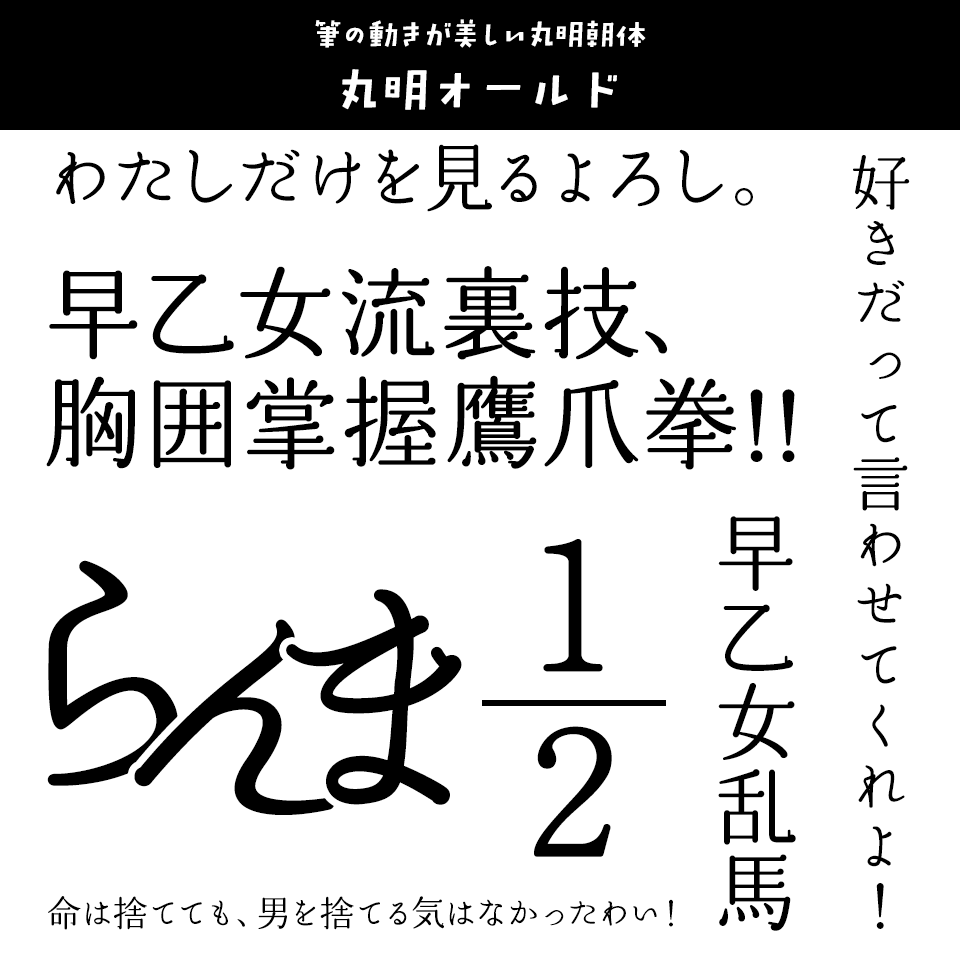
「らんま1/2」に合うフォント ティラノゴチ
らんま達の「やんちゃさ」を感じさせるデザインフォント
ティラノゴチ【ヤマナカデザインワークス】
「らんま1/2」に合うフォント ティラノゴチ
手書き文字をベースとして、やんちゃ小僧をコンセプトに作った元気系日本語フォントです。見出しやタイトル、ロゴなどにインパクトを持たせたいとき、力強く元気な印象を持たせたいときに是非お使いください。
「らんま1/2」に合うフォント パンダベーカリー
新アニメのトレーラーで見たっぽいデザインゴシック
パンダベーカリー【鈴木メモ】
「らんま1/2」に合うフォント パンダベーカリー
新アニメのトレーラーで見たようなデザインゴシックです。独特のリズム感と可愛さがらんま1/2の世界観を盛り上げます。
「らんま1/2」に合うフォント あめちゃんポップ まる
タイトルロゴに使えそうなデザイン書体
あめちゃんポップ まる【かに沢のりお】
「らんま1/2」に合うフォント あめちゃんポップ まる
まるをあちこちに散りばめた、ぽってりかわいいポップな太めのフォントです。タイトルロゴにも使えそうなまるいフォルムがかわいい。
「らんま1/2」に合うフォント やんちゃポップ
ドタバタラブコメディにぴったりの太めでポップなフォント
やんちゃポップ【かに沢のりお】
「らんま1/2」に合うフォント やんちゃポップ
やんちゃな子供をイメージした、かわいい太めのポップなフォント。OpenTypeフォントに加えTrueTypeフォントを同梱しています。漢字もたっぷり(約6700文字)収録、縦書きにも対応しています。
「らんま1/2」に合うフォント AR黒丸POP体H
らんま1/2らしい元気でインパクトのある書体
AR黒丸POP体H【アーフィック】
「らんま1/2」に合うフォント AR黒丸POP体H
黒を基調とした丸ゴシックタイプで太めの書体デザイン。らんま1/2らしい元気でインパクトのある書体です。
「らんま1/2」に合うフォント DF唐風隷書体
中華な雰囲気を作り出す隷書体
DF唐風隷書体【ダイナフォント】
「らんま1/2」に合うフォント DF唐風隷書体
らんま1/2の中華な雰囲気をフォントで作り出すなら隷書体がおすすめです。
「らんま1/2」に合うフォント 華流体
連載当時の雰囲気を漂わせるどこか懐かしいフォント
華流体【楽フォント】
「らんま1/2」に合うフォント 華流体
滑らかな運筆、一気呵成に仕上げた印象の書体。手書きと書道スタイルが組み合わされ、市井の雰囲気を出しつつ、文学的でレトロな魅力があります。
「らんま1/2」に合うフォント 丸明オールド
筆の動きが美しい丸明朝体
丸明オールド【砧書体制作所】
「らんま1/2」に合うフォント 丸明オールド
文字を構成するエレメントに丸を使っています。ゴシックに丸ゴシックがあるように、明朝体にも丸明朝体というカテゴリーがあることを実証した書体です。縦線、横線、点、トメ、ハライなどどれも先端が丸く処理されています。直線を意識した漢字、筆の動きを強調したカナ、四角いスペースにこだわらない形。でも文章になると読みやすい、不思議な可読性を持った書体です。